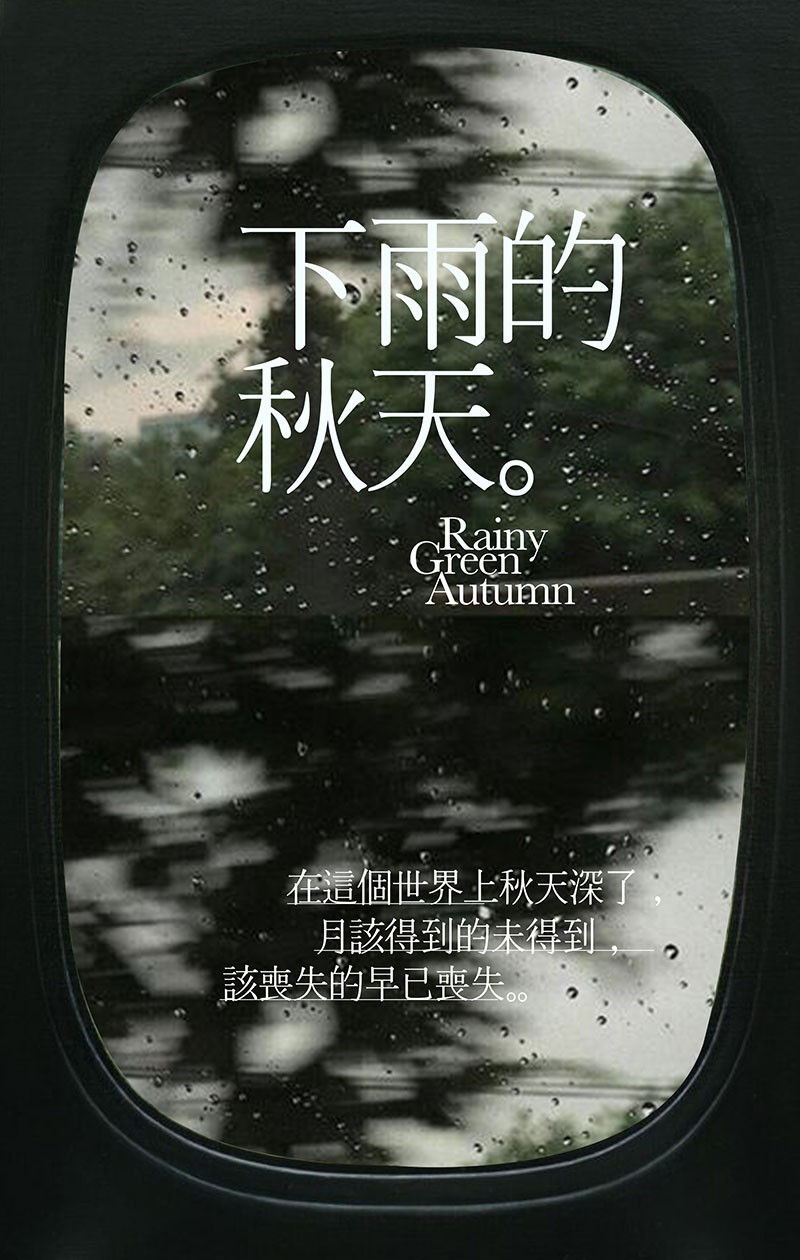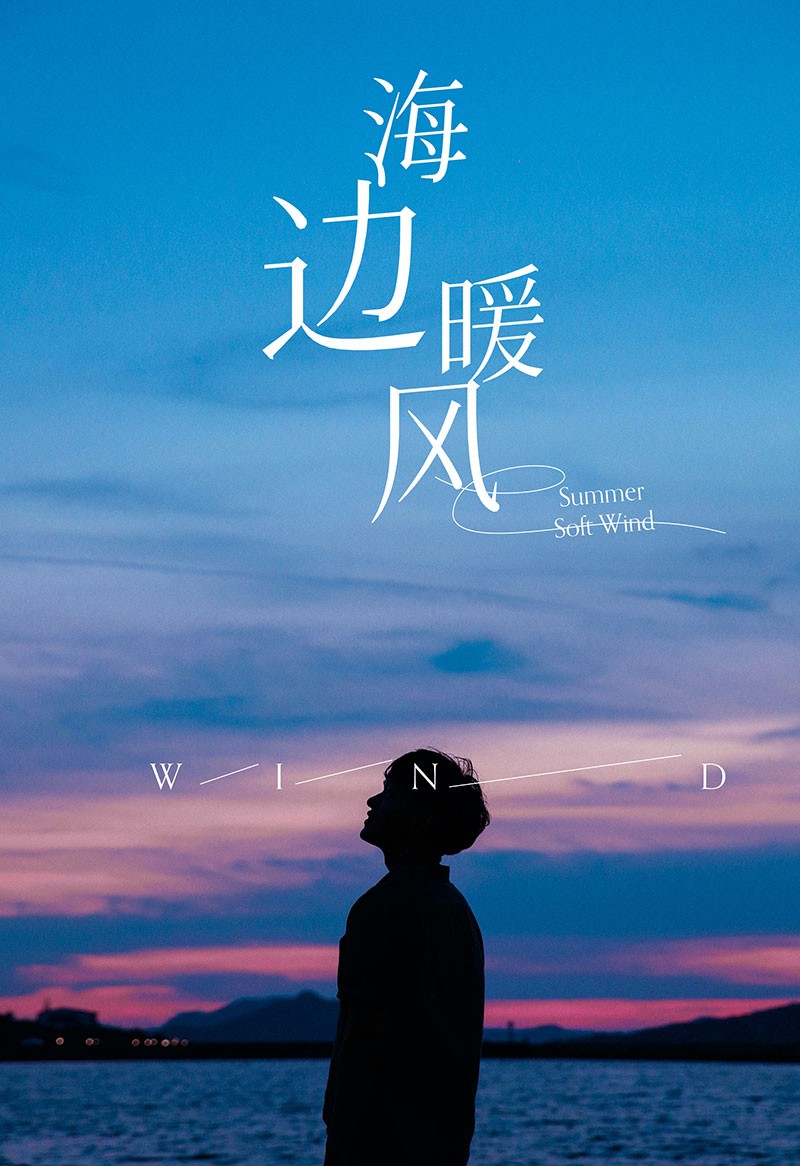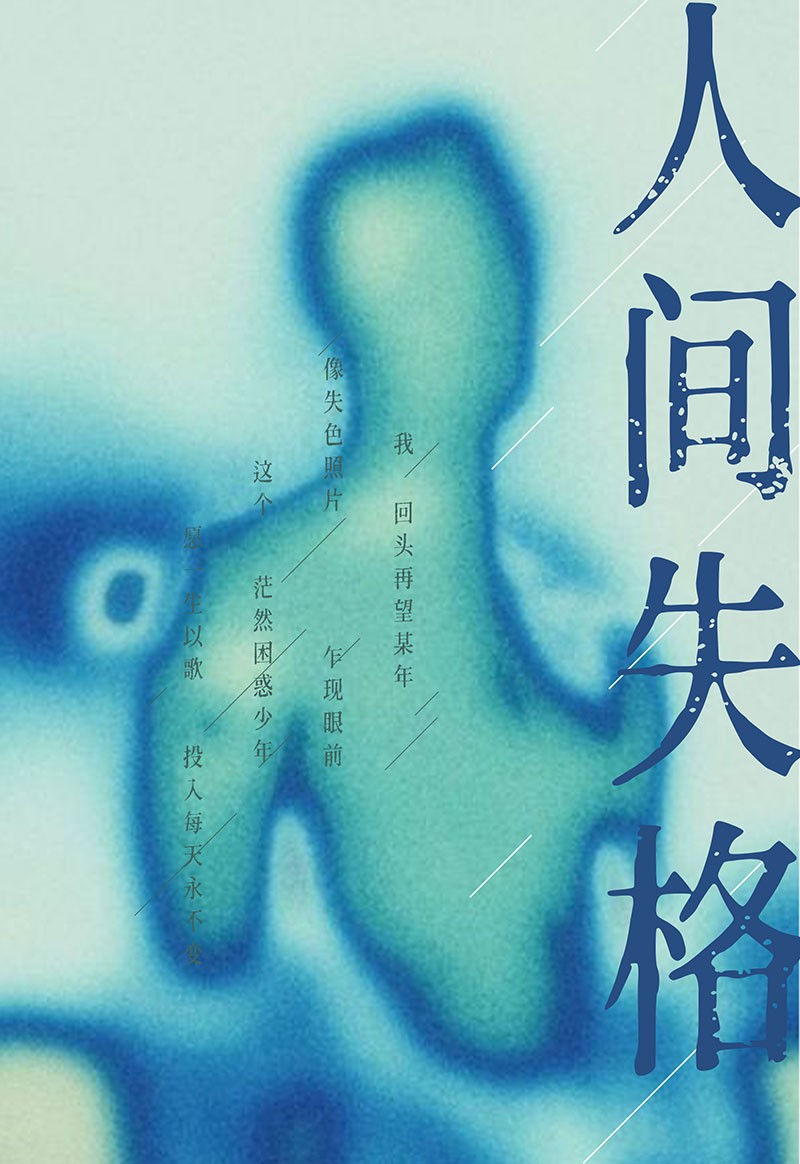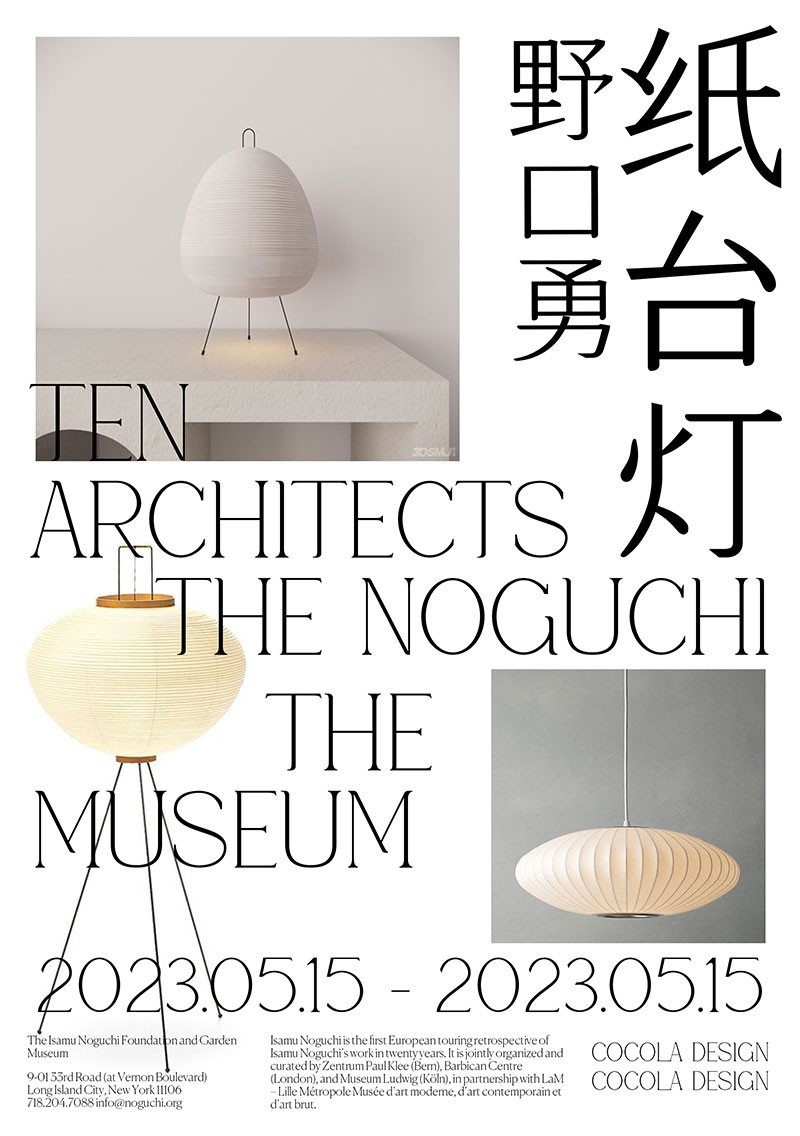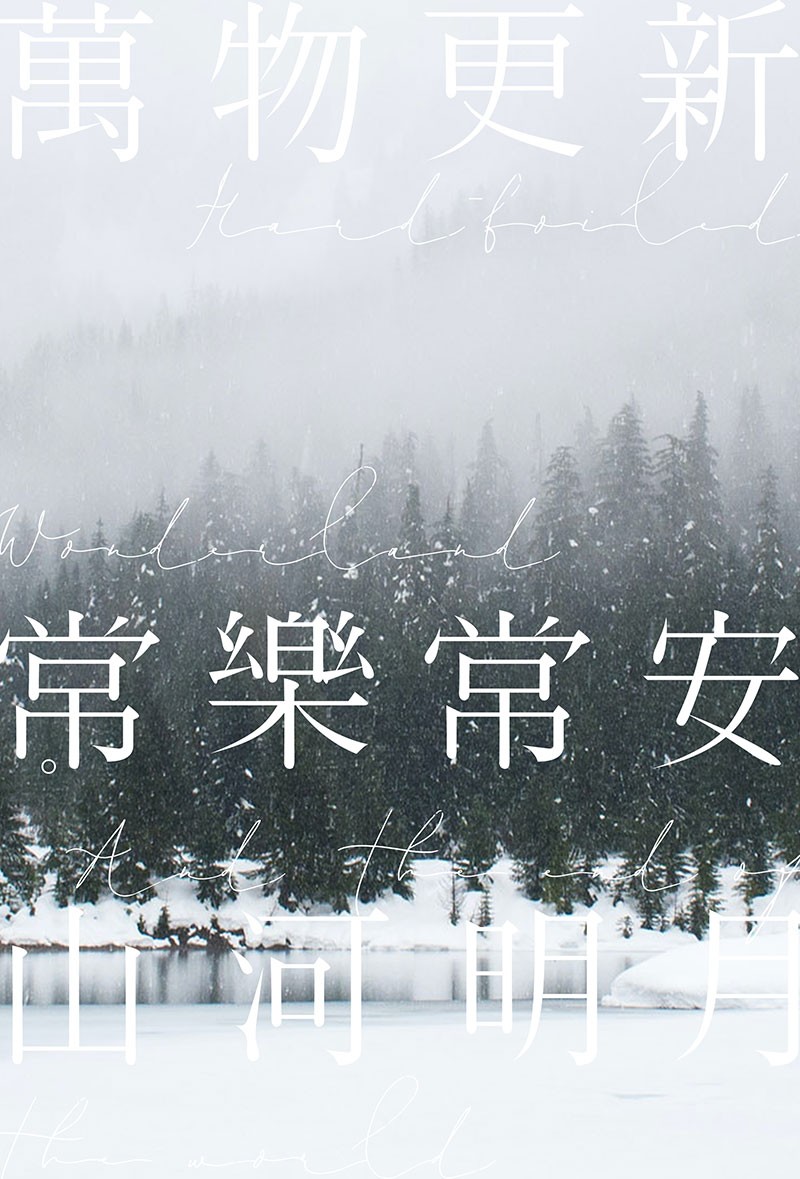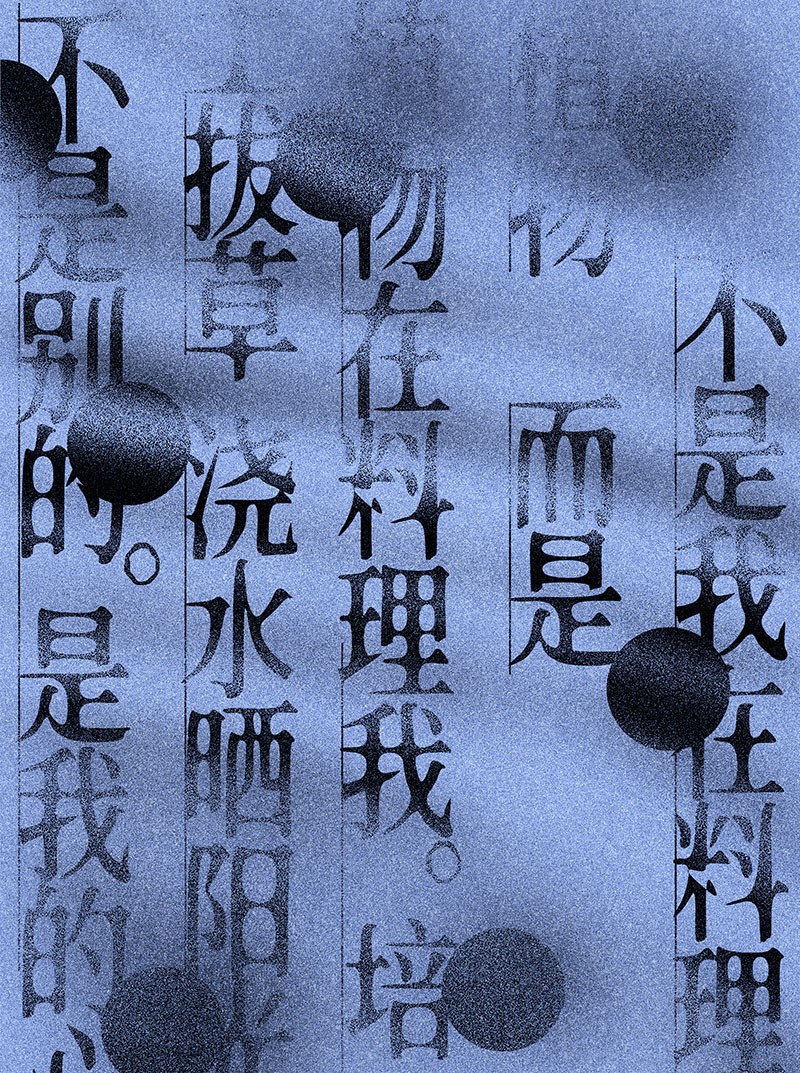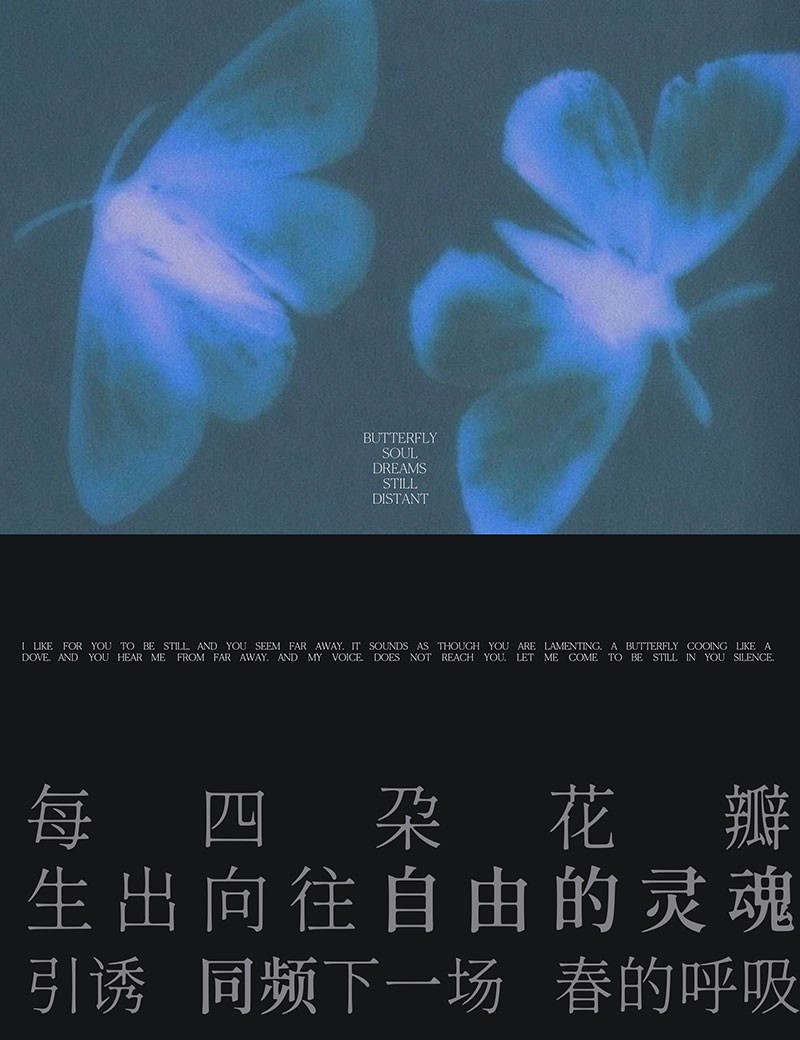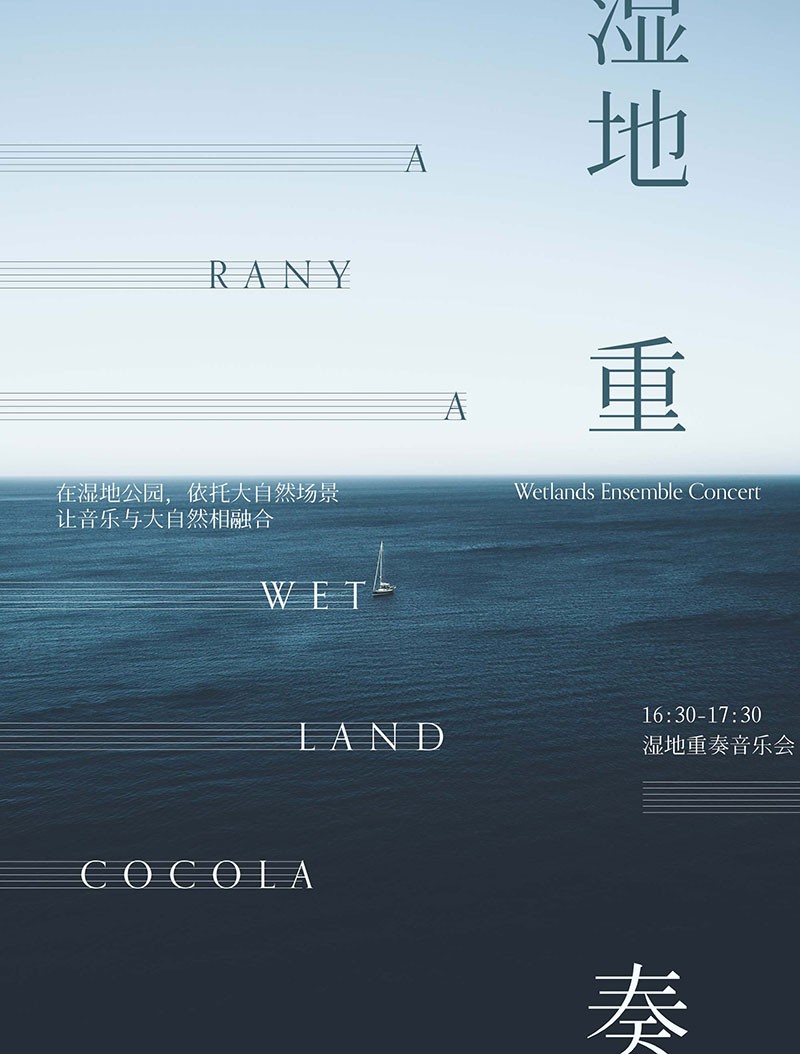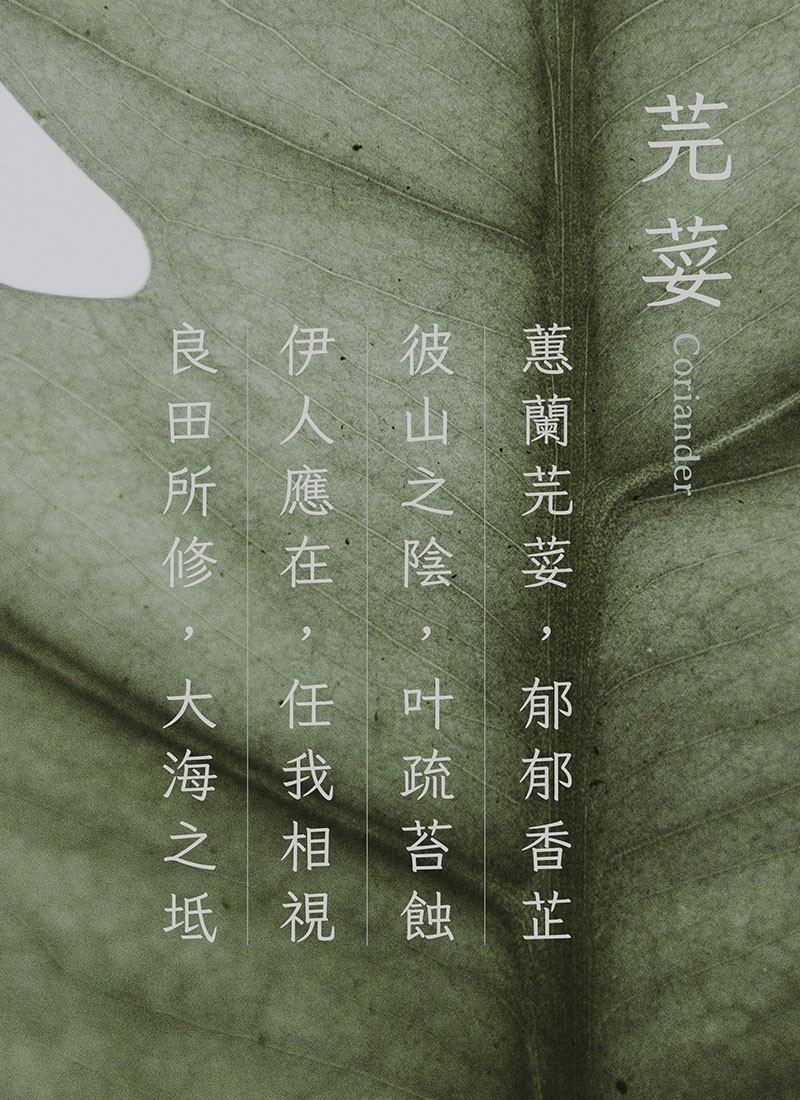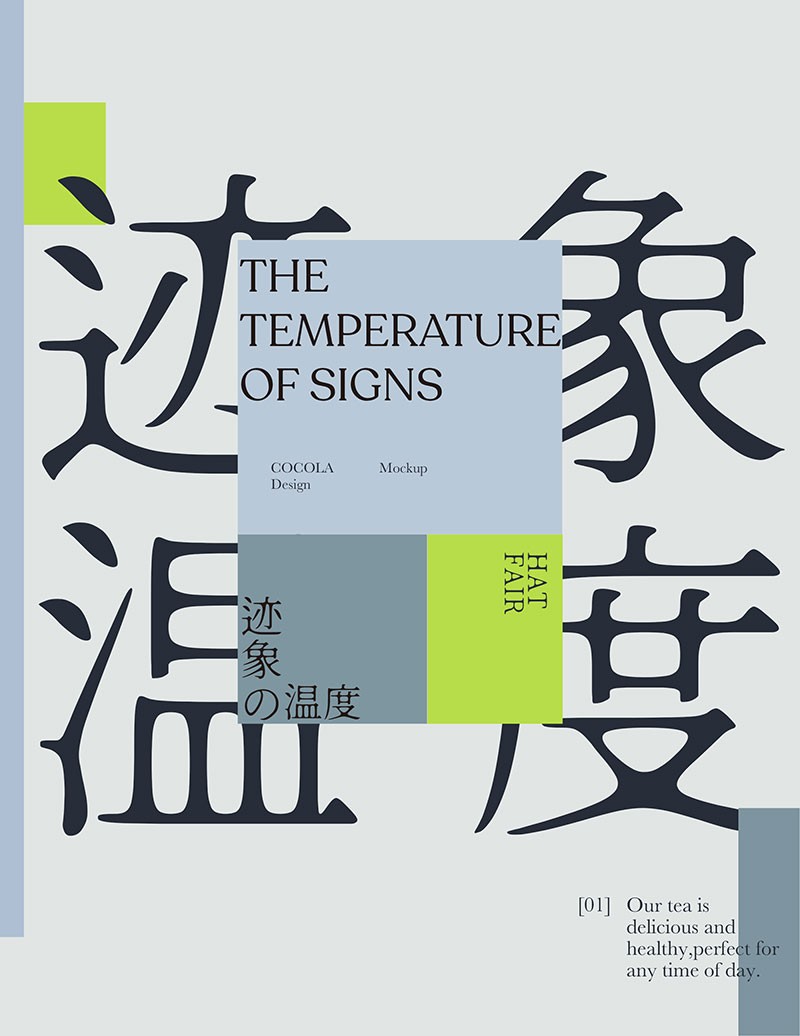
17款优质可商用的宋体字合集
从宋代雏形到明代中期的成熟定型,宋体字蕴含着深厚的文化底蕴。而在日本和韩国,宋体更被尊称为“明朝体”。素材君整理了17款简洁雅致的宋体字风格字体合集,这些字体适用于各种文艺设计、海报制作、品牌宣传等场景。而且最令人欣喜的是,它们全部可以免费商用!让您的创作之路更加便捷和自由。
以下是借助这些优雅的宋体字风格字体进行的字体排版示例,创作出独特的艺术氛围,彰显品牌的独特魅力: